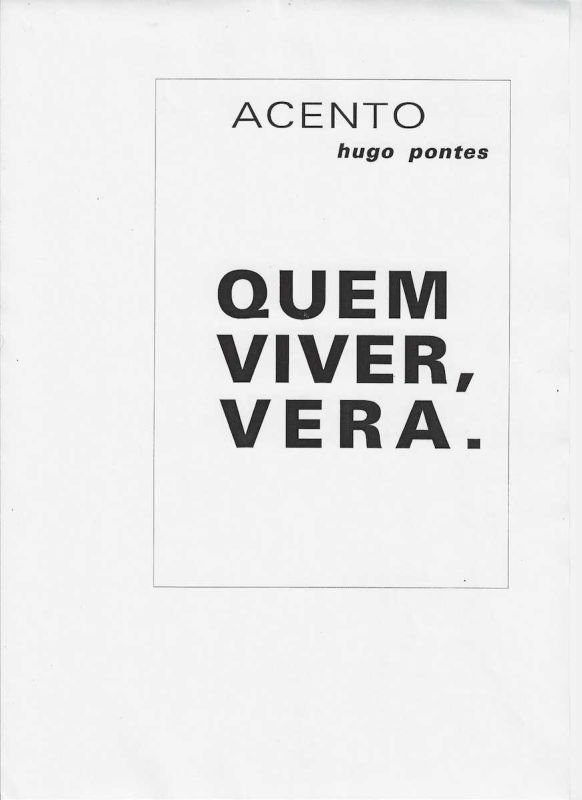
Hugo Pontes, Acento, Quem viver verá, impressão gráfica, Brasil. Obra de poesia visual construída a partir da relação entre tipografia, ortografia, linguagem verbal e percepção gráfica.
Hugo Pontes
TEXTO SALSA EM PORTUGUÊSHugo Pontes, Acento, Quem viver verá, impressão gráfica, Brasil. Obra de poesia visual construída a partir da relação entre tipografia, ortografia, linguagem verbal e percepção gráfica. A composição apresenta no alto a palavra ACENTO, acompanhada do nome hugo pontes, e no centro a frase QUEM VIVER, VERA., impressa em letras maiúsculas de grande impacto visual. A ausência do acento agudo em VERÁ constitui o núcleo conceitual da obra e transforma um elemento ortográfico em matéria poética. O título Acento orienta a leitura e evidencia a tensão entre a palavra acento e sua própria ausência na expressão popular Quem viver verá. Hugo Pontes explora assim a diferença mínima entre VERA e VERÁ, demonstrando como um sinal gráfico altera pronúncia, significado e estrutura da linguagem. A obra articula concisão, humor, metalinguagem, ambiguidade e experimentação tipográfica, aproximando poesia visual, poesia experimental, arte conceitual e comunicação gráfica. Acento integra a produção de Hugo Pontes dedicada às relações entre palavra, signo, leitura, percepção e visualidade na poesia brasileira contemporânea.SALSA TEXT IN ENGLISHHugo Pontes, Accent, Whoever lives will see, graphic print, Brazil. A work of visual poetry constructed through the relationship between typography, orthography, verbal language and graphic perception. At the top of the composition appears the word ACENTO, accompanied by the name hugo pontes, while the center presents the phrase QUEM VIVER, VERA. in large uppercase letters with strong visual impact. The absence of the acute accent in VERÁ constitutes the conceptual core of the work and transforms an orthographic element into poetic material. The title Accent guides the reading and emphasizes the tension between the word accent and its actual absence from the familiar Portuguese expression Quem viver verá. Hugo Pontes explores the minimal difference between VERA and VERÁ, demonstrating how a small graphic sign alters pronunciation, meaning and linguistic structure. The work combines concision, humor, metalanguage, ambiguity and typographic experimentation, connecting visual poetry, experimental poetry, conceptual art and graphic communication. Accent belongs to Hugo Pontes production devoted to the relationships between word, sign, reading, perception and visuality in contemporary Brazilian poetry.
TEXTO DE OBSERVAÇÃO EM PORTUGUÊSImpressão gráfica em preto sobre fundo branco de Hugo Pontes, delimitada por moldura retangular fina. Na parte superior encontra se a palavra ACENTO em letras maiúsculas, seguida abaixo e à direita pela identificação hugo pontes em tipografia inclinada. No centro da página, em caracteres negros de grande dimensão, aparece a expressão QUEM VIVER, VERA. distribuída em três linhas. A pontuação inclui vírgula após VIVER e ponto final após VERA. O aspecto fundamental da composição é a supressão do acento agudo que transformaria VERA em VERÁ, forma correta da conhecida expressão Quem viver verá. Essa ausência não funciona apenas como erro ortográfico, mas como procedimento deliberado de poesia visual e metalinguagem. O título Acento cria uma expectativa que é negada visualmente no corpo do texto, produzindo paradoxo, ironia e participação ativa do leitor. A leitura depende do reconhecimento da frase popular e da percepção imediata da falta do sinal gráfico. A obra reduz a intervenção poética a uma alteração mínima, demonstrando a força semântica e visual de um único acento. Documento relevante para estudos sobre Hugo Pontes, poesia visual brasileira, poesia experimental, poesia concreta e pós concreta, arte conceitual, tipografia, ortografia, metalinguagem, jogos de linguagem, comunicação visual e relações entre palavra escrita e imagem.OBSERVATION TEXT IN ENGLISHBlack on white graphic print by Hugo Pontes enclosed within a thin rectangular border. At the top appears the word ACENTO in uppercase letters, followed below and to the right by the identification hugo pontes in italic typography. At the center of the page, in large bold black characters, appears the expression QUEM VIVER, VERA. arranged across three lines. The punctuation includes a comma after VIVER and a final period after VERA. The fundamental aspect of the composition is the suppression of the acute accent that would transform VERA into VERÁ, the correct form in the familiar Portuguese expression Quem viver verá. This absence does not function simply as an orthographic error but as a deliberate procedure of visual poetry and metalanguage. The title Accent creates an expectation that is visually denied within the text, producing paradox, irony and active reader participation. Interpretation depends on recognizing the popular phrase and immediately perceiving the missing graphic sign. The work reduces poetic intervention to a minimal alteration, demonstrating the semantic and visual power of a single accent mark. A relevant document for studies on Hugo Pontes, Brazilian visual poetry, experimental poetry, concrete and post concrete poetry, conceptual art, typography, orthography, metalanguage, language games, visual communication and relationships between written word and image.
Hugo Pontes, Accent, Whoever lives will see, graphic print, Brazil. A work of visual poetry constructed through the relationship between typography, orthography, verbal language and graphic perception.